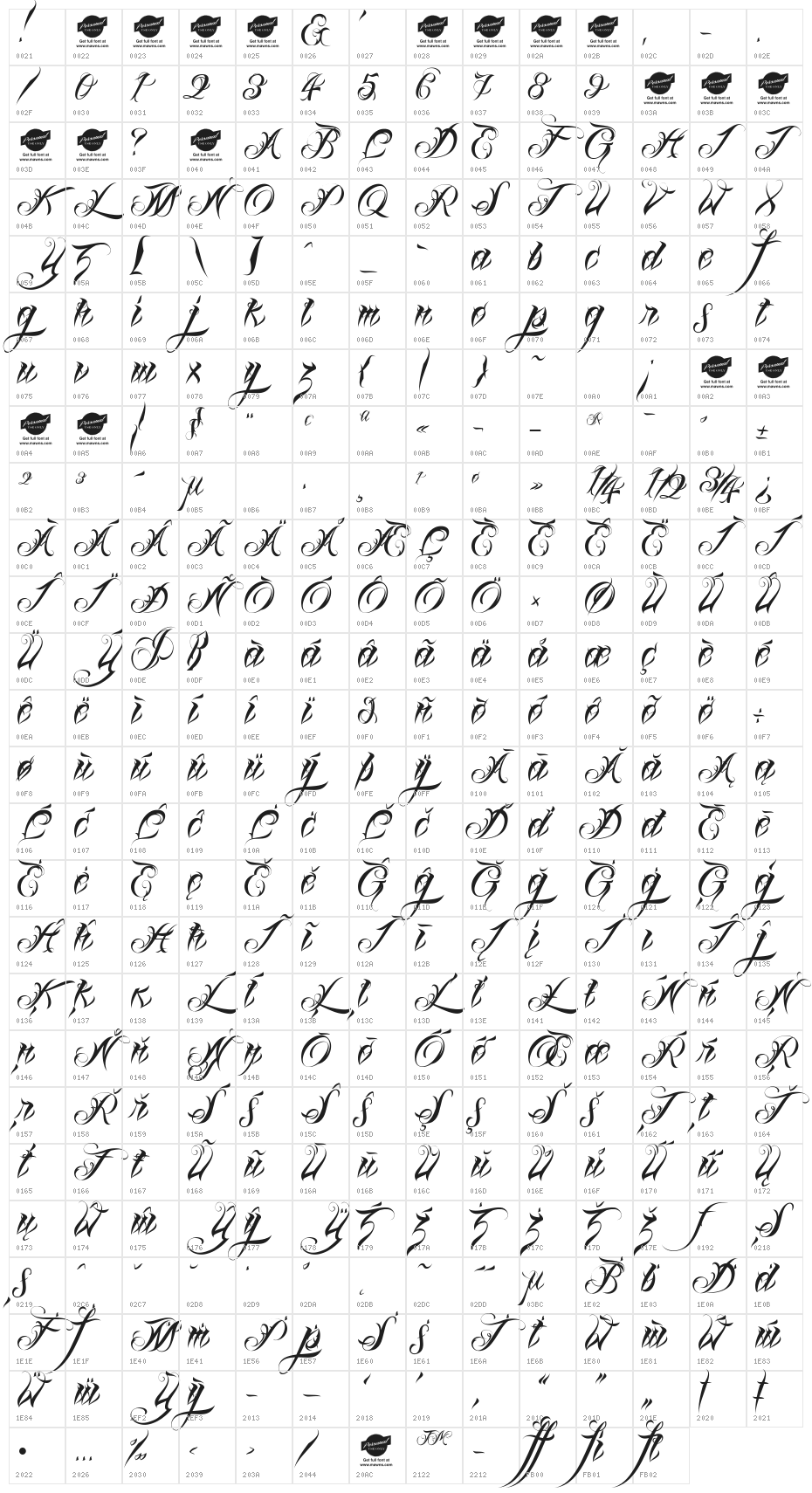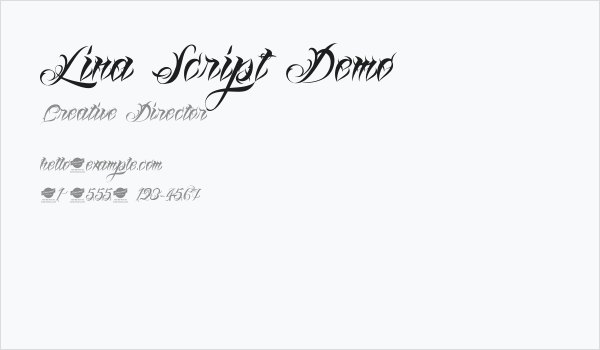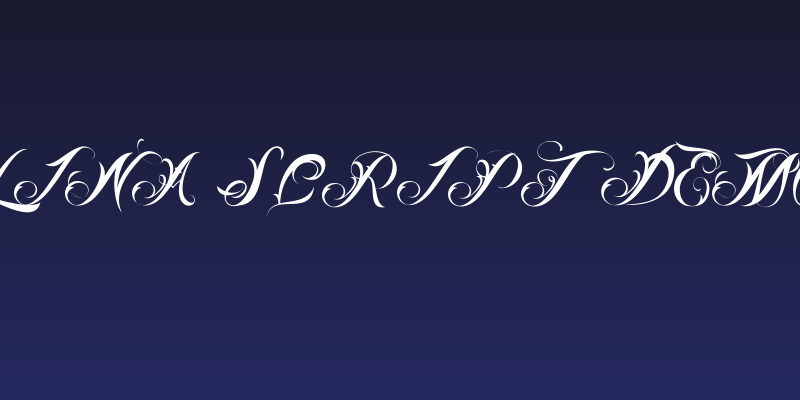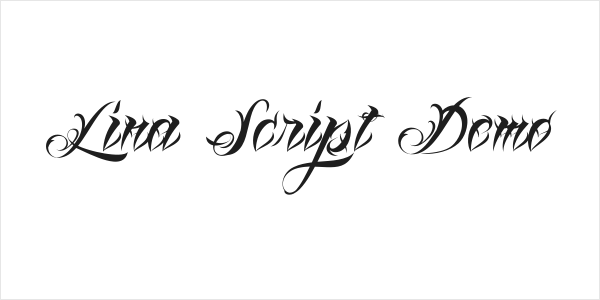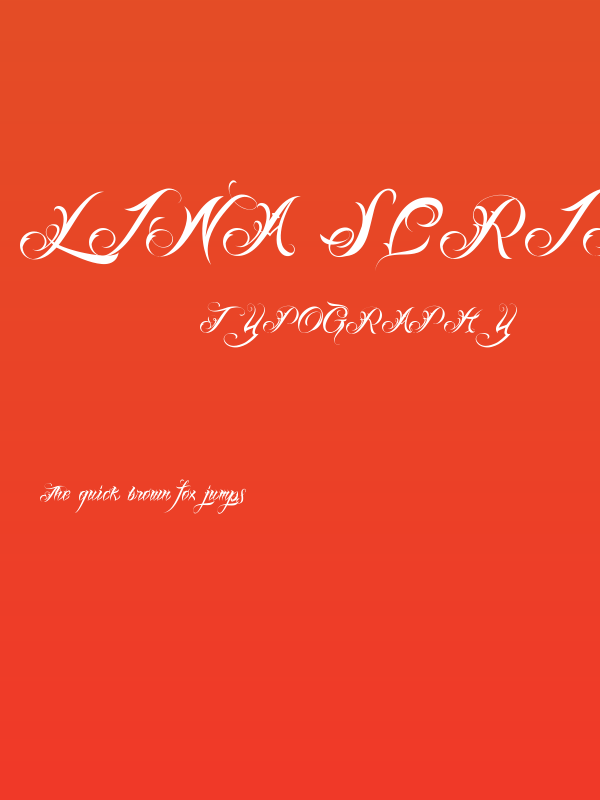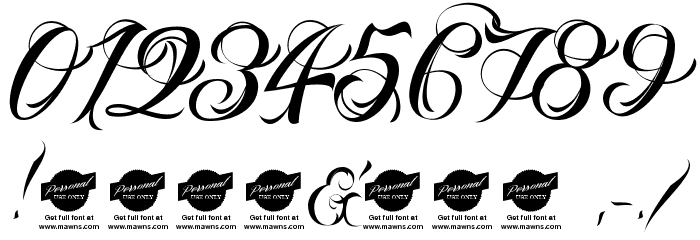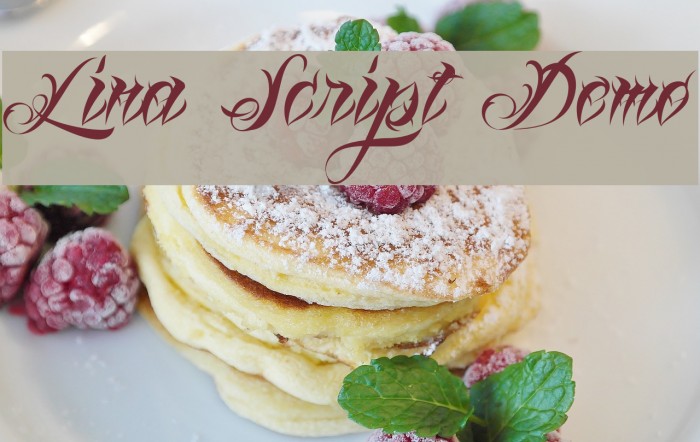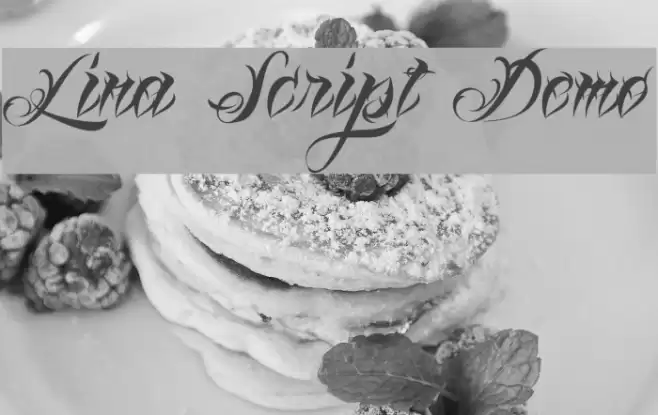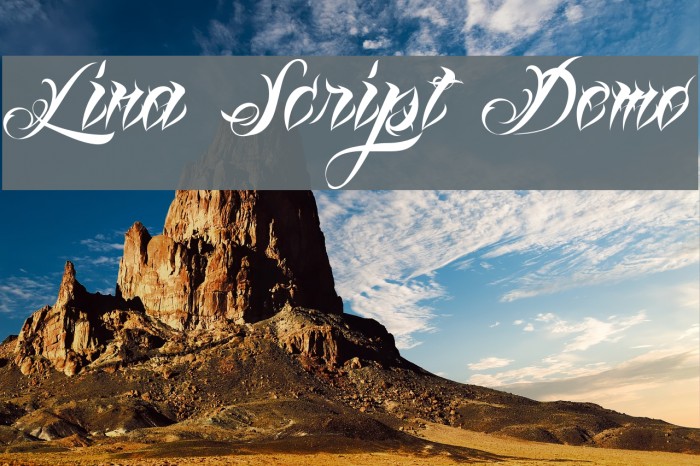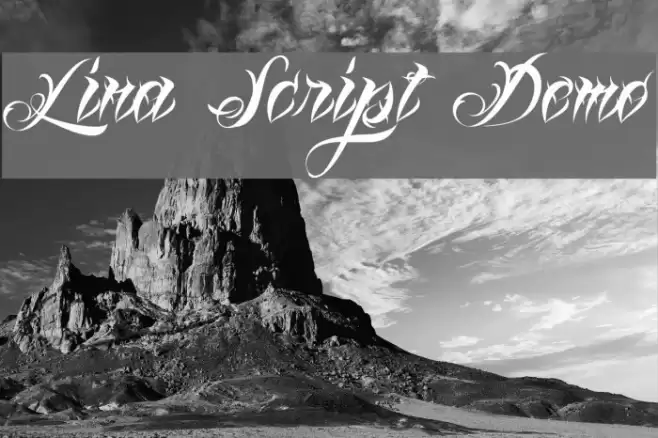
Lina Script Demo Font
✎ Script
| Anwendungsfall | Logos, Invitations, Decorative text |
| Vorgeschlagene Projekte | Ideal for wedding invitations, luxury branding, elegant packaging, and artistic posters. |